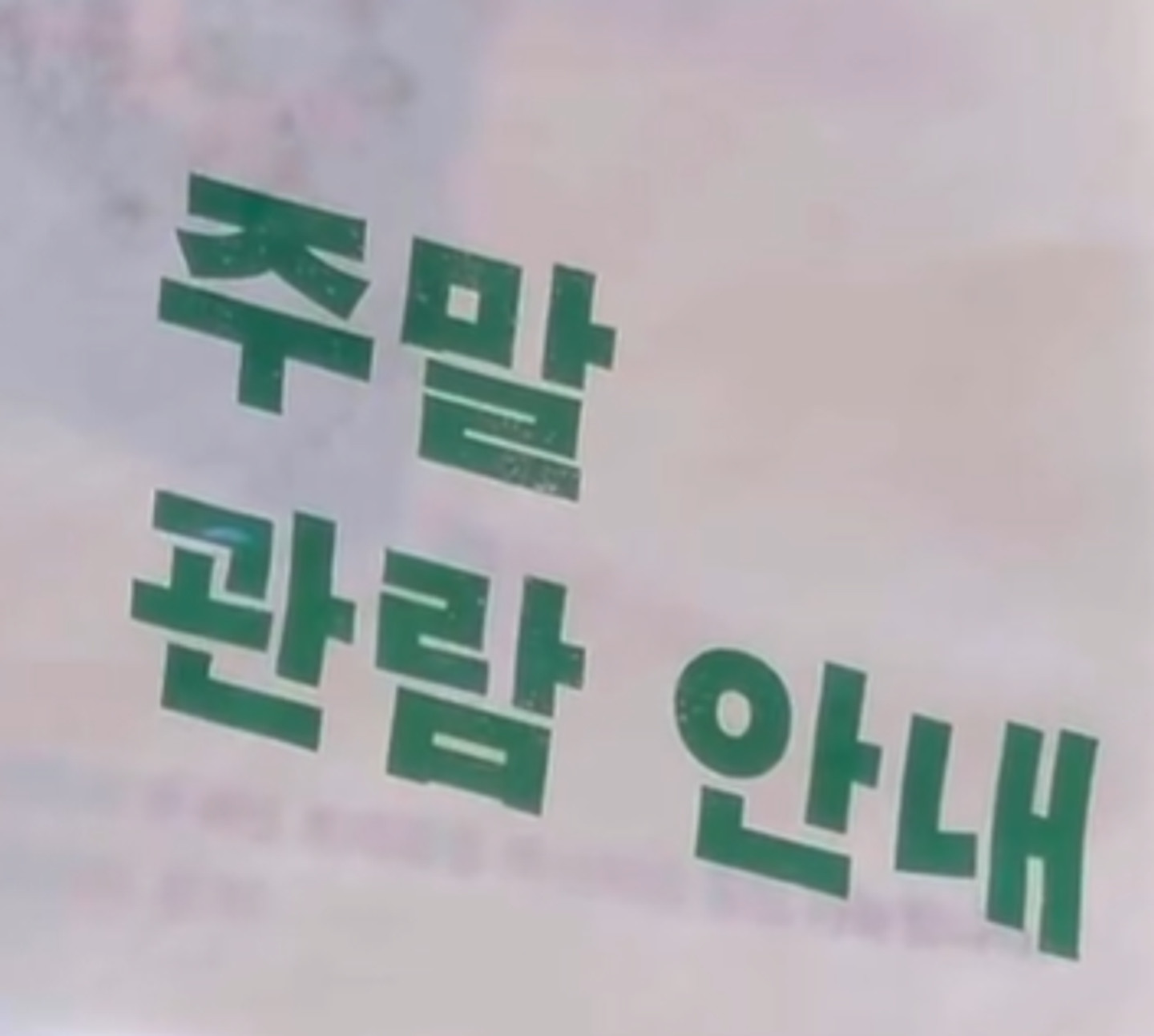
서울시립대학교 졸업전시 도록에 쓰인 폰트입니다. 편집디자인 관련해서 자주 본 것 같은데 정확히 어떤 폰트인지 궁금하네요ㅠㅠㅠ 아시는 분들 계시나요?? 약간 삐뚤어진듯 아닌듯 한게 귀엽고 재밌는 폰트입니다...
지백
https://tumblbug.com/jibaek 확실하지 않습니다. 지백은 펀딩 폰트로, 현재 판매되지 않고 있습니다. 구매 문의는 텀블벅 '창작자 문의'에서 해보시길 바랍니다. 유사한 폰트로는 Sandoll 그레타산스, AG초특태고딕 등이 있습니다.